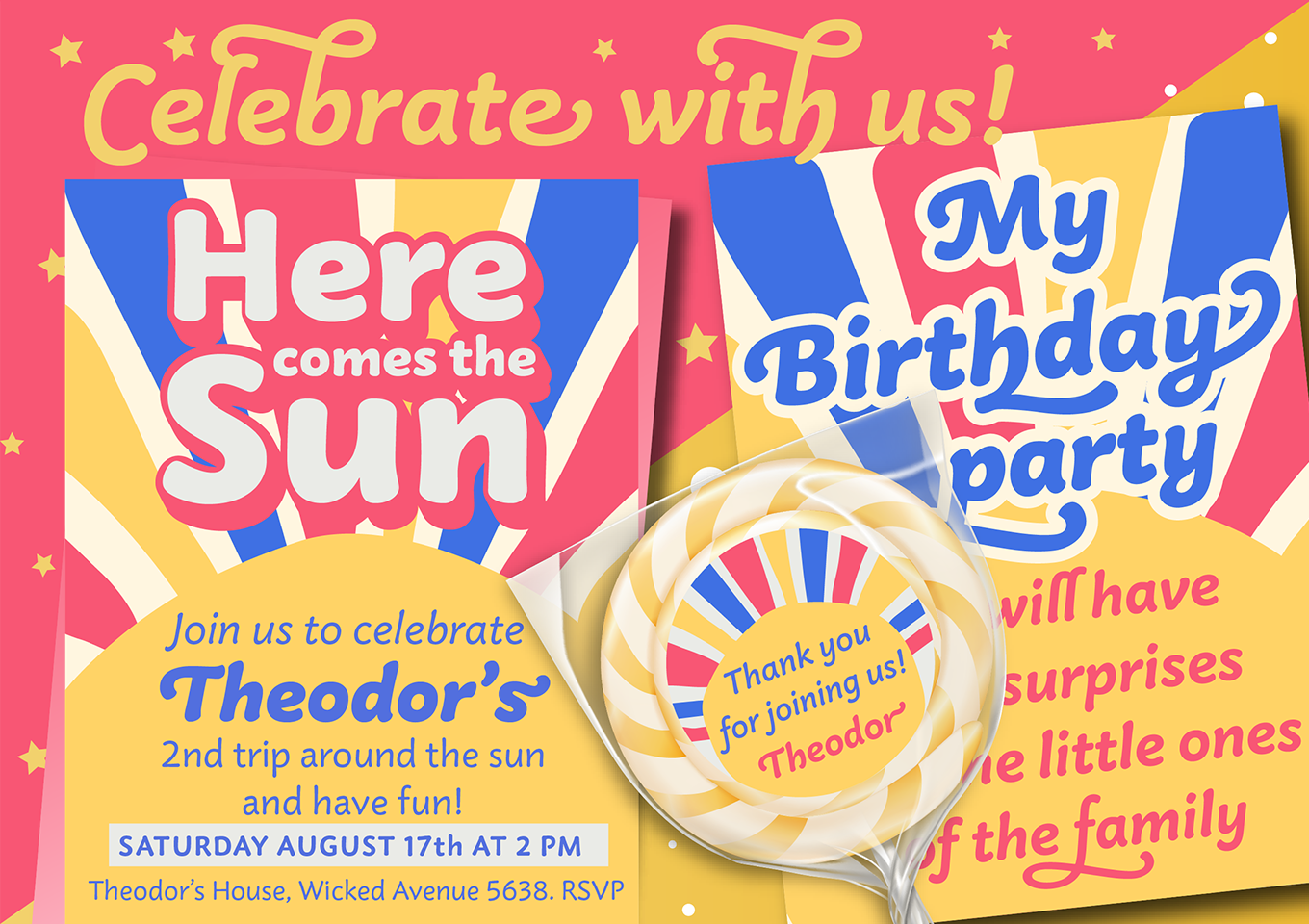
「Rocio Pro」は、「タイプデザインコンペティション 2014」欧文部門で、モリサワ賞 銅賞および明石賞に入賞した書体です(入賞時書体名:Kulin)。柔らかさを感じさせる画線、起筆・終筆部分に残るインクの溜まりのようなふくらみは、「Rocio」(スペイン語で「しずく」)の名にふさわしい、優しく豊かな表情を生み出しています。Italicには、より装飾的にデザインに活かすためのスワッシュ字形なども多数用意されており、テキストに合わせて文字のかたちを選び、表情豊かなデザインを作り上げられます。